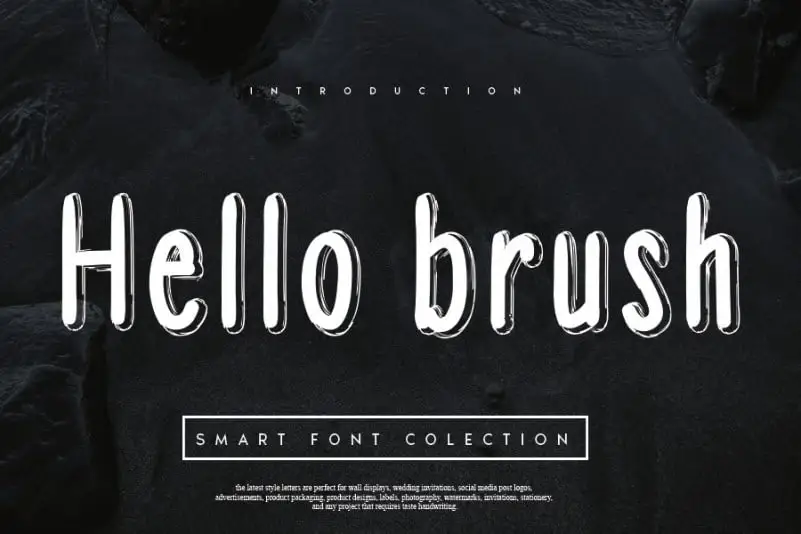
Hello brush Font – Download Grátis
A “Hello Brush Font” é uma tipografia expressiva ideal para aqueles que querem adicionar uma nota de luxo ao seu design digital. Com sua forma fluida e versátil, esta fonte traz um toque elegante a qualquer projeto, especialmente adequada para criações como cartões de casamento, arte de post-it, posts na mídia social ou até mesmo ilustrações criativas. É uma ótima escolha para aqueles que procuram adicionar um ar sofisticado e único ao seu trabalho, seja em projetos profissionais ou pessoais. Com “Hello Brush Font”, qualquer design toma vida.